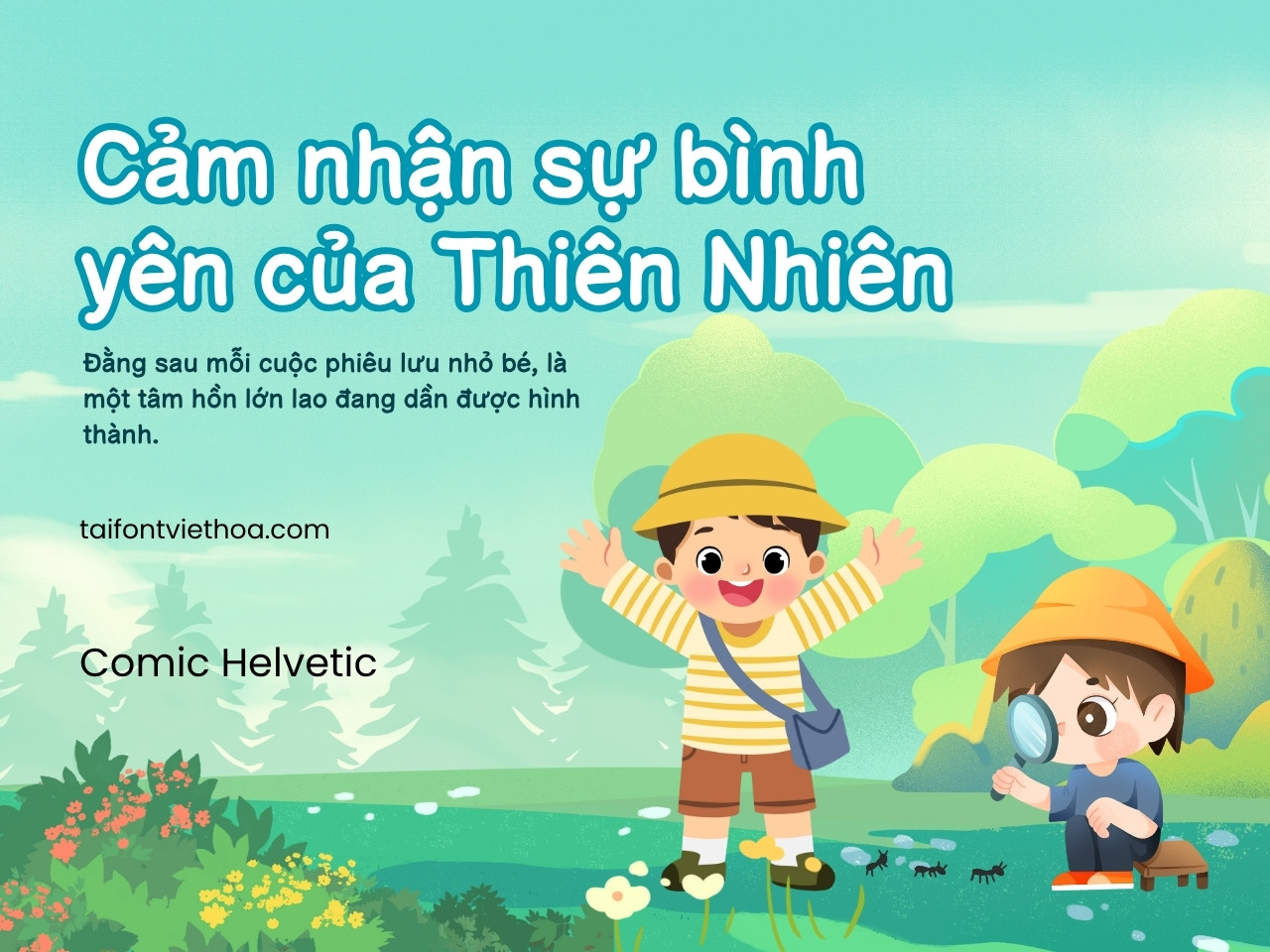
Giới thiệu font Comic Helvetic+ – Kết hợp giữa chuẩn mực Helvetic và tinh thần vui nhộn
Comic Helvetic+ là một font sans-serif phá cách, kết hợp giữa cấu trúc vững chắc của Helvetica với phong cách dí dỏm, dễ thương đặc trưng của dòng chữ comic. Font được thiết kế bởi Alexander Pravdin, một nhà thiết kế nổi bật với các bộ chữ mang tính ứng dụng cao nhưng vẫn giữ yếu tố cá tính. Phiên bản Việt hóa do Catterio thực hiện đã bổ sung đầy đủ bộ dấu tiếng Việt, đồng thời hỗ trợ hơn 90 ngôn ngữ khác. Font này đã được taifontviethoa.com sưu tầm và lựa chọn, nhằm cung cấp một lựa chọn tươi mới, vui nhộn nhưng vẫn chuyên nghiệp cho các nhà thiết kế làm việc trong lĩnh vực quảng cáo, ứng dụng số và thương hiệu hướng đến người trẻ.
Thiết kế tròn trịa, thân thiện và ứng dụng đa dạng của Comic Helvetic+
Comic Helvetic+ nổi bật với kiểu chữ sans-serif bo tròn, cấu trúc thoáng, tỷ lệ cân đối giữa các ký tự và chi tiết hài hước ở các đường nét. Font có cảm giác hiện đại, thân thiện và dễ đọc trên cả màn hình lẫn bản in. Đây là lựa chọn tuyệt vời cho các thiết kế như tiêu đề poster, banner mạng xã hội, giao diện ứng dụng trẻ em, menu thực đơn vui nhộn, hoặc các chiến dịch marketing cho thương hiệu trẻ trung. Font đặc biệt phù hợp với các ngành như công nghệ, giáo dục, ẩm thực, thương mại điện tử, truyền thông sáng tạo và các dịp như Valentine, Trung thu, sinh nhật hoặc các sự kiện dành cho giới trẻ.